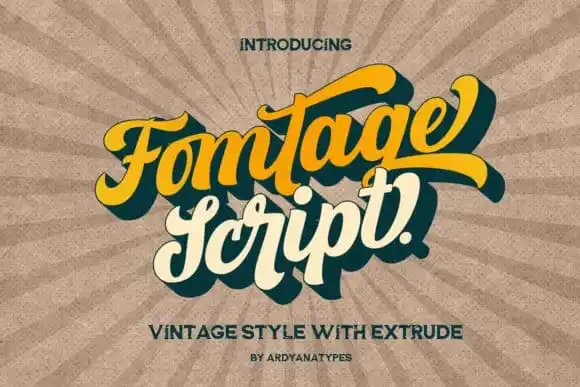
Fomtage Script Font – Download Grátis
A Fonte Fomtage Script é uma criação do designer ardyanatypes que oferece uma experiência visual agradável e fluida. Com seu estilo script, este texto retrata um toque elegante que se assemelha à escrita manuscrita de quem usa suas mãos para escrever. Este tipo de fonte traz consigo aquela sensação nostálgica leve e aconchegante dos tempos passados. Perfeita tanto para design gráfico quanto para criação de logotipos ou outras ideias de design, ela oferece um toque autêntico do mundo vintage aos seus projetos. Essa fonte é perfeitamente indicada para aqueles buscando adicionar uma nota especial e retro a qualquer projeto que tenha em mente. É ideal para designers buscando dar um toque único à sua próxima obra de arte visual, seja ela um aplicativo móvel, um site web ou até mesmo uma camiseta personalizada. Fomtage Script pode ser usada para criar uma atmosfera nostálgica e retrô que certamente vai deixar seu design mais atraente e memorável.